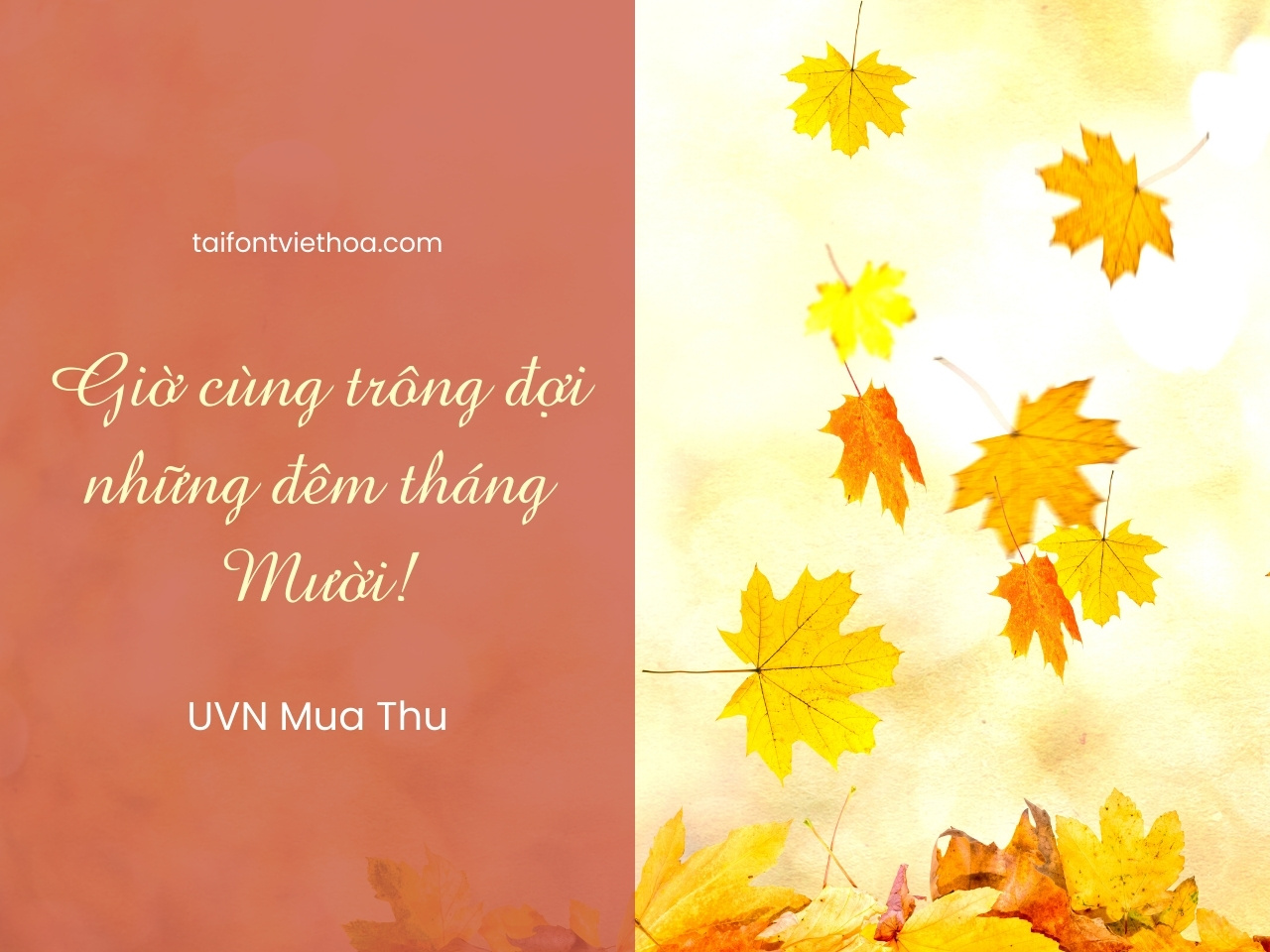
Font việt hóa UVN Mua Thu
Giới thiệu về font UVN Mua Thu
UVN Mua Thu là một font chữ mang đậm chất thơ và cảm xúc, lấy cảm hứng từ mùa thu – mùa của hoài niệm, của sắc vàng dịu nhẹ và những cơn gió se lạnh. Tên gọi “Mùa Thu” gợi lên một không gian nhẹ nhàng, trầm lắng và có phần mộng mơ, rất phù hợp với những thiết kế thiên về cảm xúc, nghệ thuật và nội dung trữ tình. Font được sưu tầm và chia sẻ bởi thành viên Font Chuẩn, đồng thời được taifontviethoa.com chọn lọc kỹ lưỡng nhằm phục vụ các dự án sáng tạo, in ấn thơ ca, thiết kế thiệp, sách tâm sự và truyền thông mang tính cá nhân hóa.
Đặc điểm thiết kế và ứng dụng của UVN Mua Thu
Font UVN Mua Thu có phong cách handwritten pha lẫn script nhẹ nhàng, với các nét uốn lượn tinh tế, độ dày vừa phải, tạo cảm giác mềm mại và tự nhiên. Các ký tự được cách điệu mềm, nghiêng nhẹ như những dòng chữ viết tay mang tâm trạng. Font hỗ trợ tiếng Việt đầy đủ và dễ dàng sử dụng trên cả nền in ấn lẫn kỹ thuật số.
Ứng dụng lý tưởng: sách thơ, nhật ký, thiệp mời, poster truyền cảm hứng, bìa sách trữ tình. Ngành nghề phù hợp: xuất bản, nghệ thuật, truyền thông cảm xúc, thiết kế thiệp cưới và sản phẩm handmade mang yếu tố lãng mạn, hoài cổ.